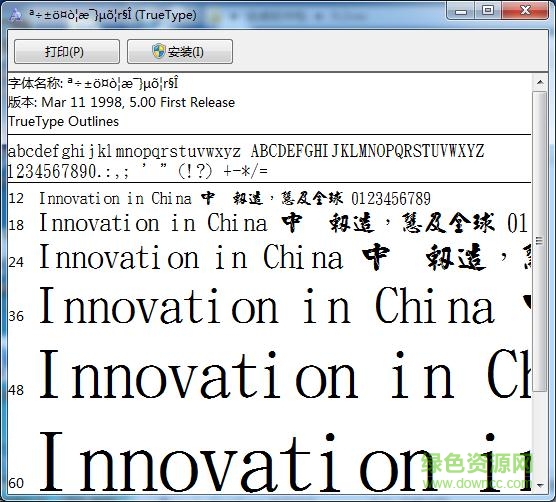
軟件介紹 軟件標(biāo)簽: 金梅 破裂字體 字體 金梅毛行破裂字形是金梅字體中的一張裂痕字體。字體帶有破裂的效果,并且還有毛筆字書法的效果,總體感覺不錯,也經(jīng)常被用于廣告設(shè)計。趕快下載體驗吧!字體使用方法將字體文件復(fù)制到C:\Windows\Fonts文件夾即可完成安裝(Win7用戶可直接右鍵選擇“安裝”菜單進(jìn)行安裝)。小編推薦裂痕字體大全:http://m.lz0519.com/k/liehenziti/ 軟件截圖 上一張下一張(1 / 1) 安裝詳細(xì)截圖 猜你喜歡 金梅字體 裂痕字體 金梅字體 金梅字體是以繁體字形為主,多數(shù)的金梅字體都是繁體。金梅字體給人的感覺比較多樣,有的比較圓潤,有的比較可愛,還有破裂的字體,于楷體形成了鮮明的對比,沒有固定的樣式。金梅字體多用于廣告制作、海報制作、封面制作等。 查看更多>> winman tun10011字體 17.57M/中文/6.6/下載 金梅浪漫原體國際碼 1.91M/中文/6.6/下載 金梅粗明原體國際碼 1.41M/中文/5.0/下載 金梅流行書 2.78M/中文/10.0/下載 金梅綜藝菱心 4.19M/中文/10.0/下載 金梅浪漫小胖 3.44M/中文/10.0/下載 裂痕字體 裂痕字體又叫破裂字體,簡單的來說就是將文字加上裂痕,做成破裂或撕裂效果。霹靂字體其實也屬于裂痕字體,只是給文字加上閃電劃破的效果,實際效果跟裂痕字體差不多。裂痕字體會給人一種撕心裂肺,或者說是破碎,傷心的感覺。 查看更多>> 金梅特黑裂開體字體 2.25M/中文/3.4/下載 金梅顏楷破裂字形 3.87M/中文/10.0/TTF格式下載 金梅超黑破裂字體 2.40M/中文/5.0/下載 金梅超明破裂字形 3.61M/中文/3.3/TTF版下載 金梅顏楷破裂字形(繁) 3.87M/繁體/10.0/下載 金梅毛行破裂字形(繁) 3.71M/中文/10.0/TTF版下載 其他版本下載 標(biāo)題 大小 更新日期 下載 下載地址 電腦版 金梅毛行破裂字形字體 點擊報錯 軟件無法下載或下載后無法使用,請點擊報錯,謝謝! 關(guān)閉報錯反饋 請描述您所遇到的錯誤,我們將盡快予以修正,謝謝! *必填項,請輸入內(nèi)容 本類最新 金梅海報美工體 金梅新箭頭字范例字體 免費(fèi)版 金梅特黑水花字形字體 免費(fèi)版 金梅粗尖頭字范例繁體字體 免費(fèi)版 金梅淡古字ttf 免費(fèi)版 金梅浪漫鏡射體 相關(guān)文章 Photoshop字體安裝使用方法和技巧 如何解決“無法新增字體”問題 Win 7系統(tǒng)安裝字體方法 網(wǎng)頁字體大小設(shè)置方法 怎么改網(wǎng)頁字體大小 在Linux系統(tǒng)中安裝字體的幾種方法 windows7字體顯示問題:打開某些程序的時候顯示的是亂碼 用戶評論 熱門評論 最新評論 發(fā)表評論 查看所有評論(0) 昵稱: 請不要評論無意義或臟話,我們所有評論會有人工審核. 字?jǐn)?shù): 0/500 (您的評論需要經(jīng)過審核才能顯示)